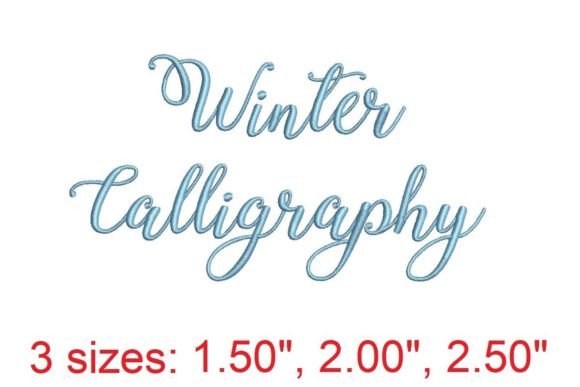
Winter Calligraphy Embroidery Font
Если вы ищете высококачественные ресурсы, такие как Winter Calligraphy Embroidery Font, этот премиум-пакет — фантастический выбор для ваших творческих проектов.
Создаете ли вы продукты POD (печать по требованию), свадебные приглашения или графику для социальных сетей, Winter Calligraphy Embroidery Font станет идеальным выбором.
Совет эксперта: комбинируйте эти элементы с дополняющими шрифтами, чтобы создавать уникальные, привлекательные дизайны, выделяющиеся на рынке.